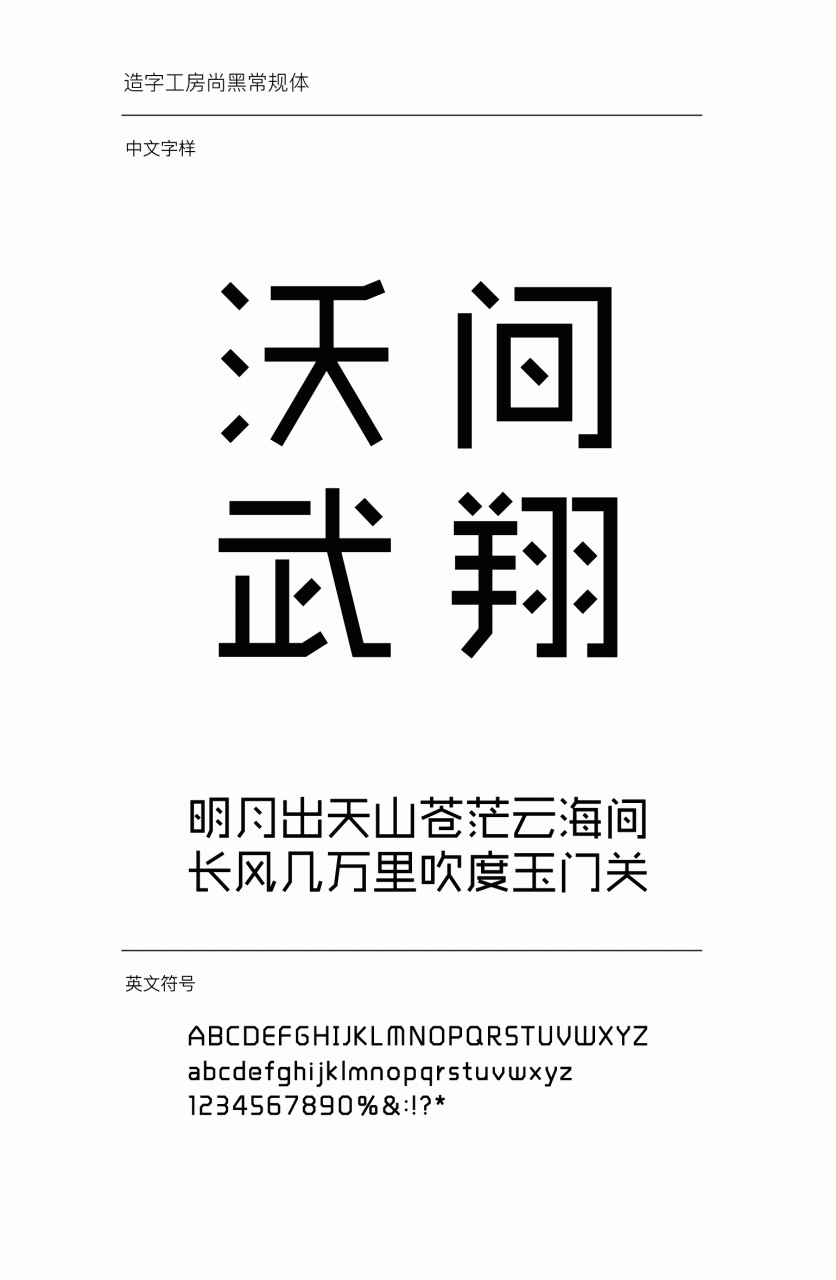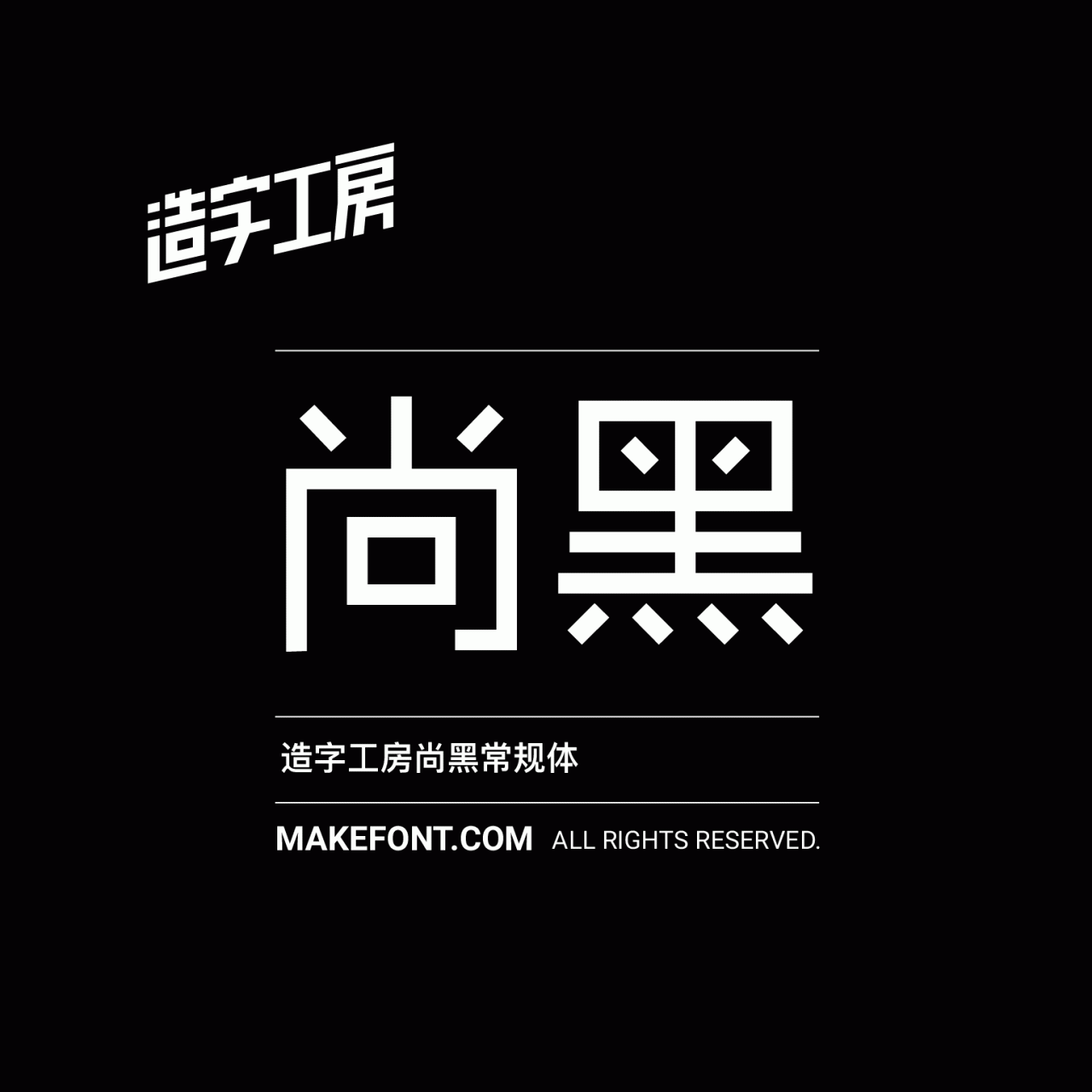
造字工房尚黑常规体设计说明 造字工房尚黑系列字体个性鲜明,设计感强,字形特点时尚新颖。全部笔画采用直线设计,打破传统字体设计局限,灵活多变的线条造就此款字体的与众不同。适用标题与广告以及Logo用字,且对设计师的选择应用有一定挑战性。 本系列字体共12款,为简体字库,采用OpenType/CID 格式, Adobe-GB1-5编码。基于中华人民共和国GB2312-80字符集标准, 另按需添加了 101 个汉字。共收容字数 6864 CJK 汉字,ASCII常用字符100个。字体下载地址点击下载 发布日期 2019年11月17日 发布于 书法字体 上篇文章: 英文书法字体Short Baby,粗体英文书法字体 下篇文章: 造字工房悦黑纤细长体 发表回复 取消回复要发表评论,您必须先登录。